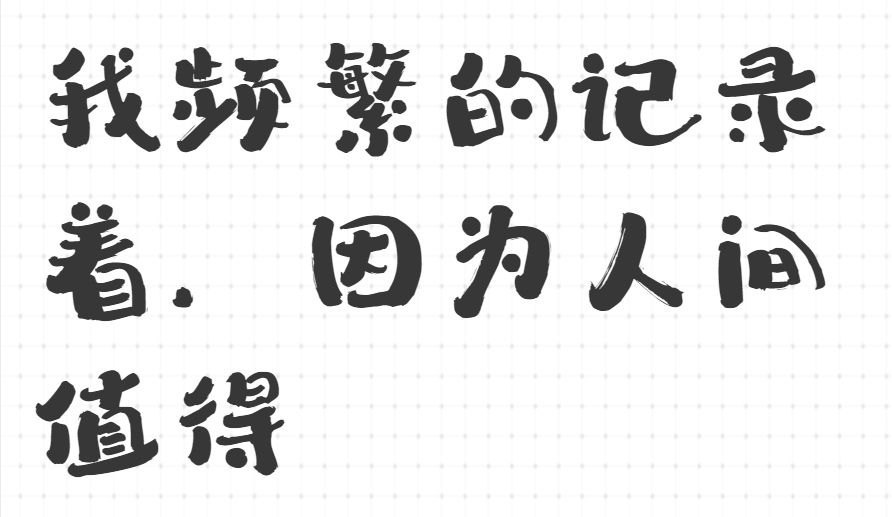
可爱书法字体,让文字散发独特魅力!
当我们谈论书法字体时,我们可能会想到那些庄重、古老、充满历史感的字体。但是,有没有一种书法字体,既能体现传统韵味,又具有现代感和趣味性呢?今天,我们要为大家介绍的就是这样一种字体,造字侠醉春风简繁一款可爱的书法字体。
它是一种融合了传统书法元素和现代卡通风格的字体。这种字体通常具有圆润的线条,可爱的形状,以及充满活力的色彩。它适合用于各种场合,如儿童书籍、动画电影、广告设计等。
与传统书法字体相比,可爱书法字体的线条更加圆润,给人一种温柔、可爱的感觉。也可以通过使用鲜艳的色彩,如粉色、蓝色、绿色等,让文字更加生动活泼。在形状和结构上往往充满创意,能够激发人们的想象力。字体设计独特,但通常都易于阅读,不会给读者带来困扰。
总之,可爱书法字体是一种充满趣味性和创意性的字体。它既具有传统书法的韵味,又具有现代感和时尚感。无论是在儿童书籍、动画电影、广告宣传还是社交媒体等领域,可爱书法字体都能发挥出其独特的魅力,让文字更加生动有趣、引人注目。